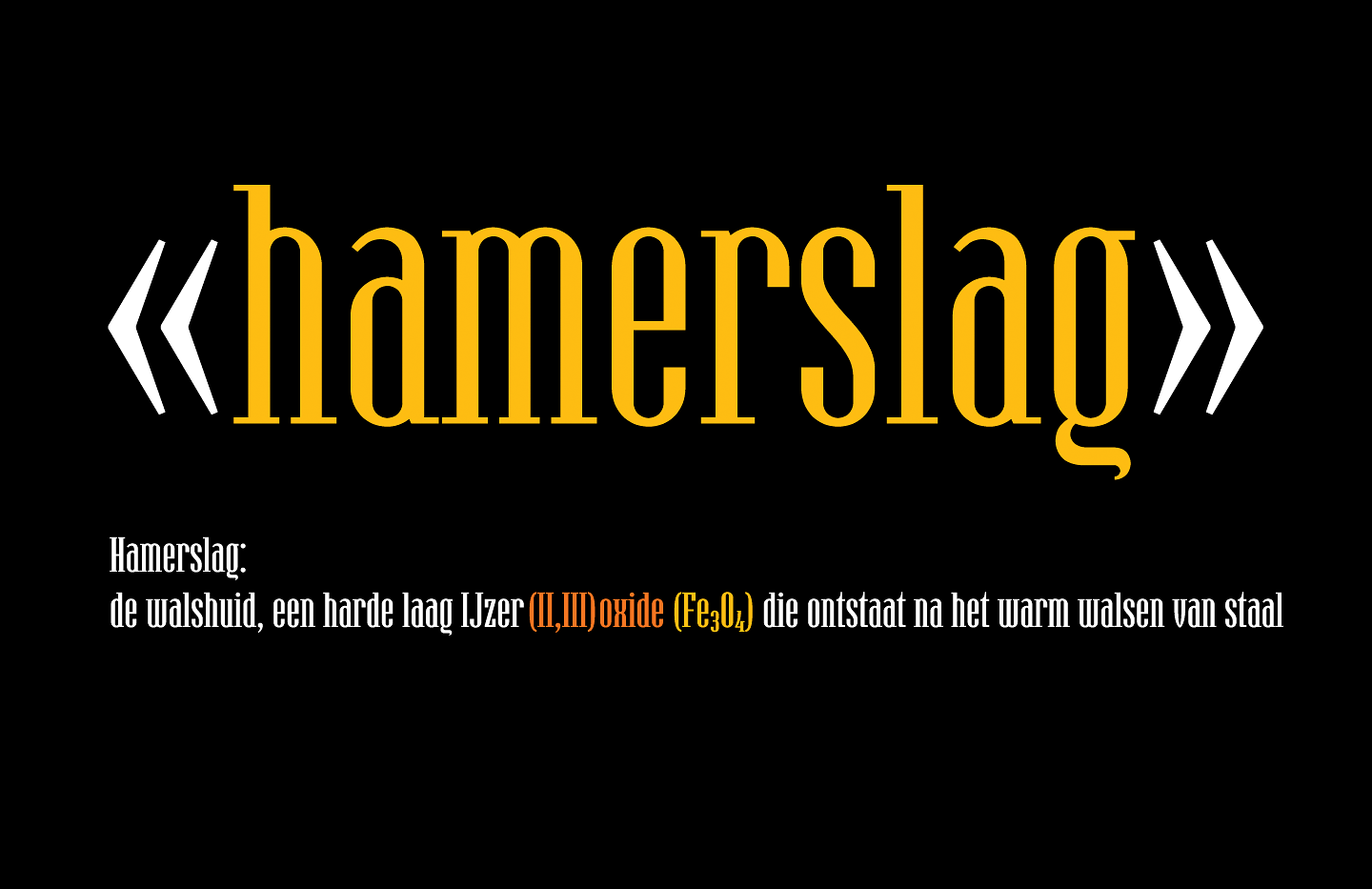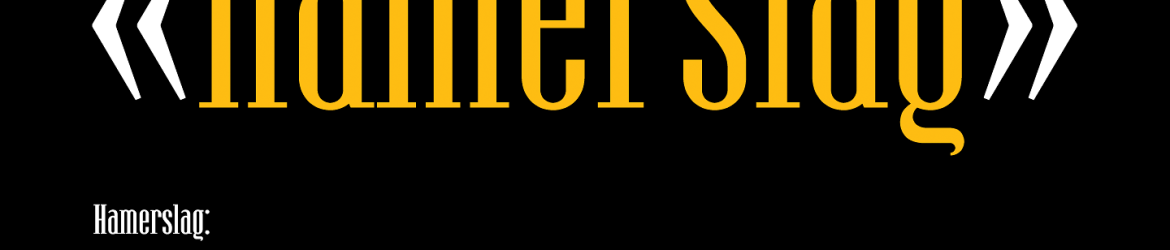
A Hamerslag Typeface é uma família de fontes serifas ultra-condensadas projetada pelo designer polonês Paweł Burgiel. Com seu estilo moderno e formas geométricas, a Hamerslag oferece um apelo romântico ainda mais forte. Esta tipografia possui um x-altura considerável, o que lhe confere uma aparência elegante e profissional. Além disso, contém figuras numerárias para fracionários e científicos, ligaturas de símbolos monetários, além de números arredondados e alinhados proporcionalmente. Ideal para design gráfico moderno, a Hamerslag oferece uma variedade de opções que complementam perfeitamente qualquer projeto visual.